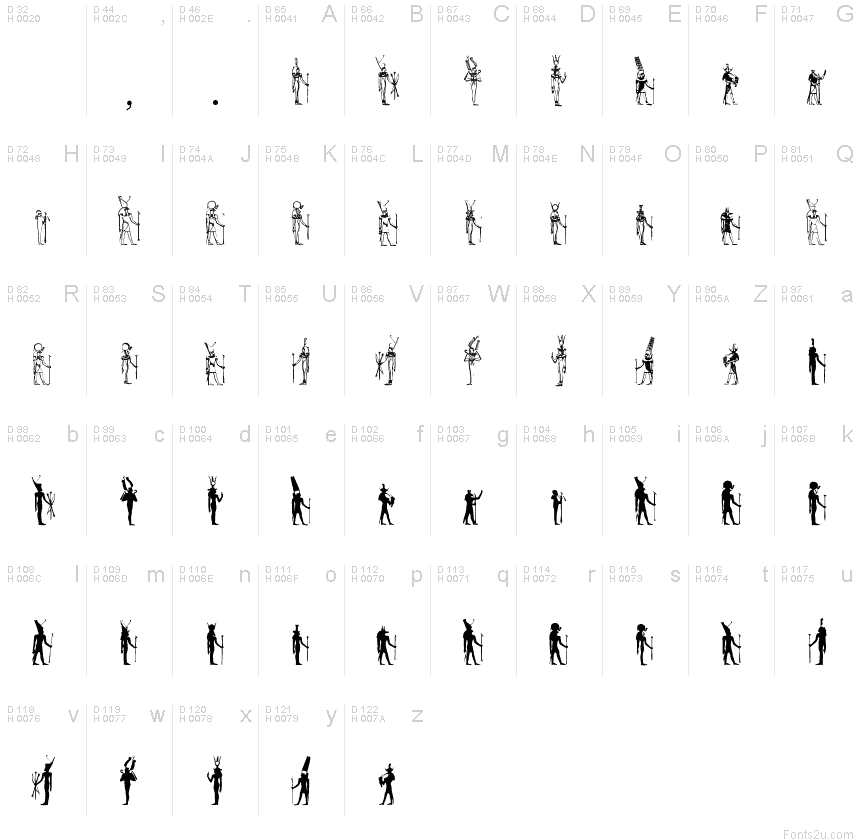
Visit the Nil Манфреда Кляйна — это бесплатный символьный шрифт (дингбат) в древнеегипетском стиле, составленный из высоких фигур в профиль. В силуэтах выделяются чётко очерченные головные уборы, посохи и удлинённые конечности, а мелкие внутренние детали отведены лицам, воротникам и одежде. Каждый символ воспринимается как компактный фрагмент настенной росписи.
Благодаря изображениям фараонов, божеств и участников церемоний шрифт отлично подходит для музейно-образовательных программ, исторических игр и мероприятий, посвящённых Египту. В издательском деле его можно использовать для оформления глав или иллюстрированных рамок, однако ярче всего он раскрывается в учебных материалах, где узнаваемые позы с первого взгляда передают древнеегипетскую эстетику и служат иллюстрациями, а не привычным текстом.